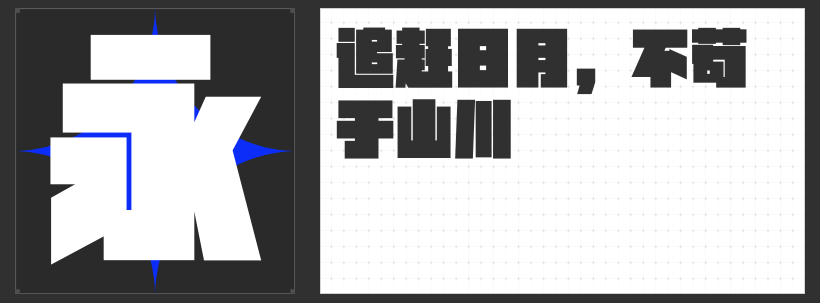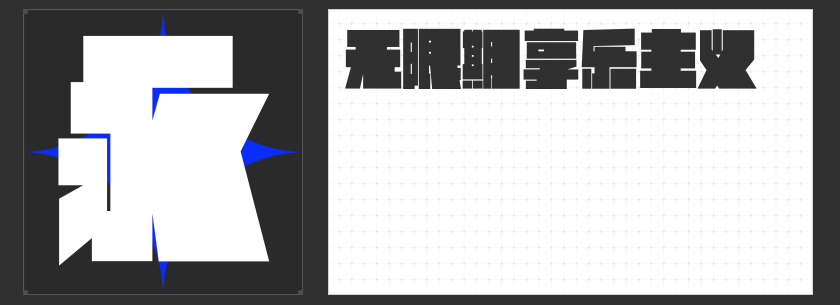
四款专业字体推荐:为汽车设计注入精准视觉力量
在汽车行业设计中,字体不仅是信息载体,更是品牌调性与产品气质的视觉化表达。选择一款契合车型定位的字体,能瞬间传递速度感、科技感或豪华感。以下四款商用字体以独特的设计语言,成为汽车视觉设计的得力伙伴。
1. 励字开拓者简 超级黑
这款字体以方正字型与超大中宫构建稳重基底,横平竖直的直线笔画如机械构件般精准。平切起收笔与均匀的内部空间处理,赋予其工业设计的理性美感;去钩化笔画与竖直化撇捺,则强化了镜像对称的视觉冲击。在汽车设计中,它尤其适合SUV或皮卡车型的广告标题——棱角分明的笔画呼应硬派车身线条,简约风格与金属质感相得益彰,传递出可靠与力量的品牌内核。
2. 造字侠灵霄简繁 传神
灵感源自《西游记》灵霄宝殿的这款字体,以硬挺笔触与古风劲萧的字形,为汽车设计注入东方美学基因。其饱满均匀的结构布局与沉稳笔力,恰似传统书法与现代工艺的融合。当高端车型或国潮概念车需要文化赋能时,这款字体可完美契合——无论是水墨风格宣传片标题,还是限量版车型的篆刻式徽标,其笔力劲健的特质都能凸显车型的稀缺性与艺术价值。
3. 励字暴风简 超级黑
作为一款突破传统的现代黑体,它以梯形分布的横竖笔画与不规则粗细对比,打破常规认知。撇捺中的梯形元素如切割空气的刀锋,横竖笔画的错落感则暗示着速度的轨迹。在电动汽车或未来概念车的设计中,这款字体能强化科技感——粗犷与精致并存的笔触,既像电路板的几何纹路,又似数据流的动态轨迹,完美匹配智能驾驶时代的视觉语言。
4. 励字宽边黑简 超级黑
通过左细右粗的极致对比与规整方正的字型,这款字体创造出独特的视觉张力。横平竖直的笔画如建筑梁柱般坚实,粗细对比则赋予其雕塑般的立体感。在豪华车型或旗舰SUV的设计中,它可成为视觉焦点——加粗的右侧笔画如同车身的肌肉线条,细左侧则隐喻空气动力学的轻盈,整体传递出沉稳而不失灵动的豪华气质。
汽车设计是理性工程与感性美学的平衡,而字体则是这一平衡的视觉注脚。无论是需要传递力量感的硬派车型,还是彰显文化底蕴的国潮座驾,这四款字体都能通过精准的设计语言,将品牌理念转化为可触摸的视觉符号。选择对的字体,便是为汽车设计注入灵魂的第一步。